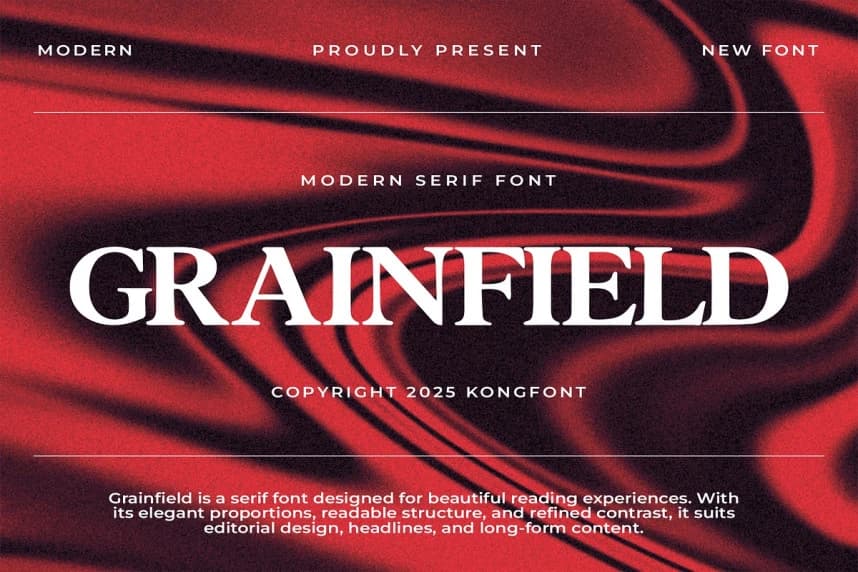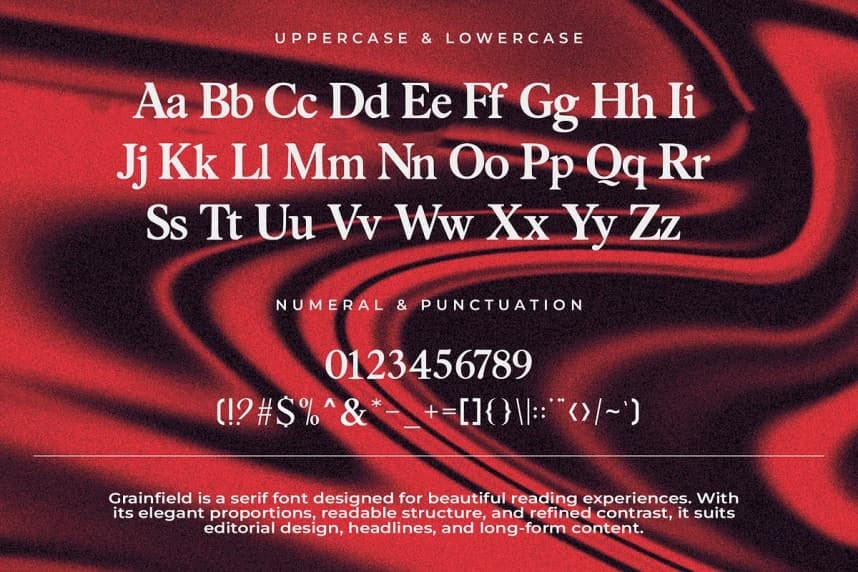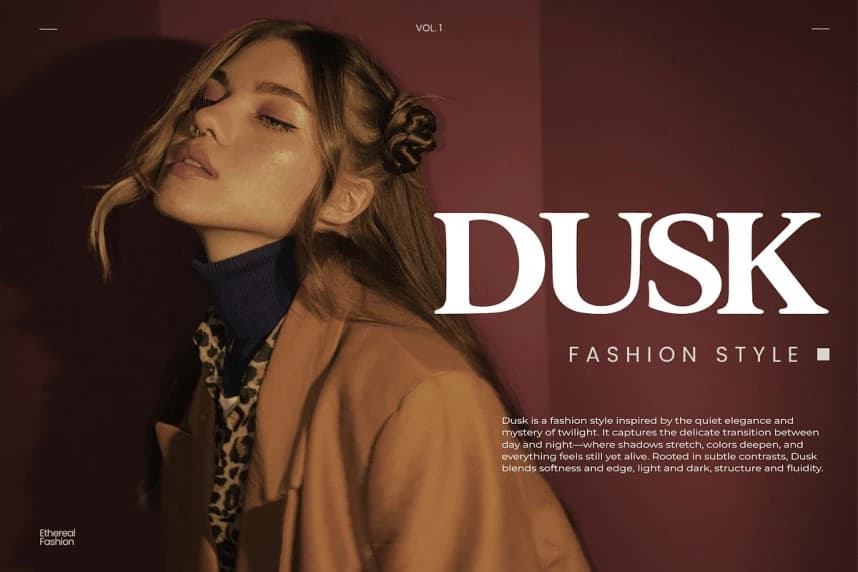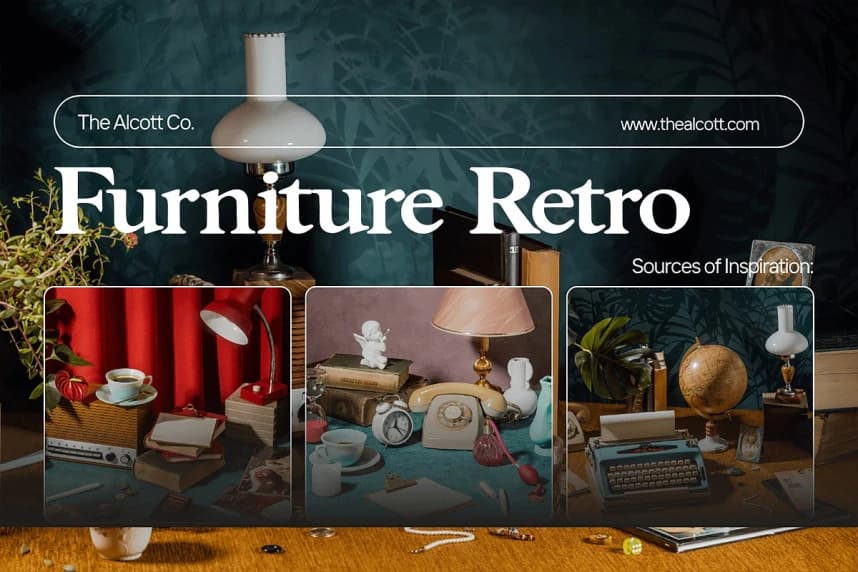
Grainfield Font
Grainfield Font, rustik çekiciliği ince zarafetle harmanlayan modern bir serif yazı tipidir. Yumuşak eğriler, dengeli kontrast ve zarif seriflerle tasarlanmıştır; bu yazı tipi tasarım projelerinize sıcaklık ve profesyonellik duygusu katıyor.
Grainfield Font, rustik çekiciliği zarif bir sofistikasyonla harmanlayan modern bir serif yazı tipidir. Pürüzsüz eğriler, dengeli kontrast ve zarif seriflerle tasarlanmıştır. Bu yazı tipi tasarım projelerinize sıcaklık ve profesyonellik hissi katar.